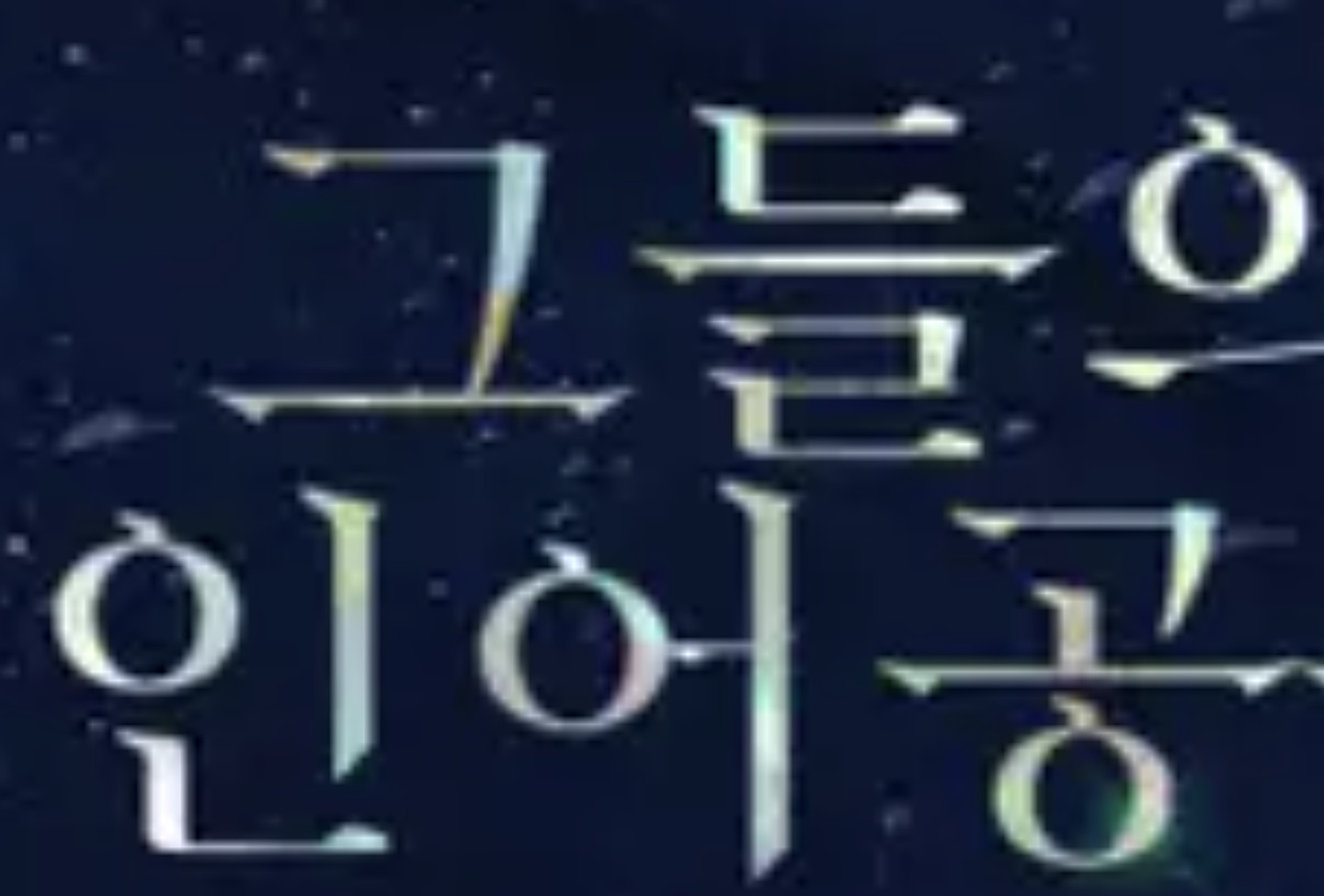
혹시 이폰트가 아시아 순명조 폰트인가요? 아니면 비슷한 이런 무료폰트 추천 부탁드립니다!
310안삼열체
310안삼열체에서 획 끝을 변형한 것입니다.
310안삼열체
비슷한 폰트 추천드립니다! 무료폰트중에서는 많이 유사한 폰트는 못찾았습니다. 결제하시려면 산돌도 괜찮아보입니다!